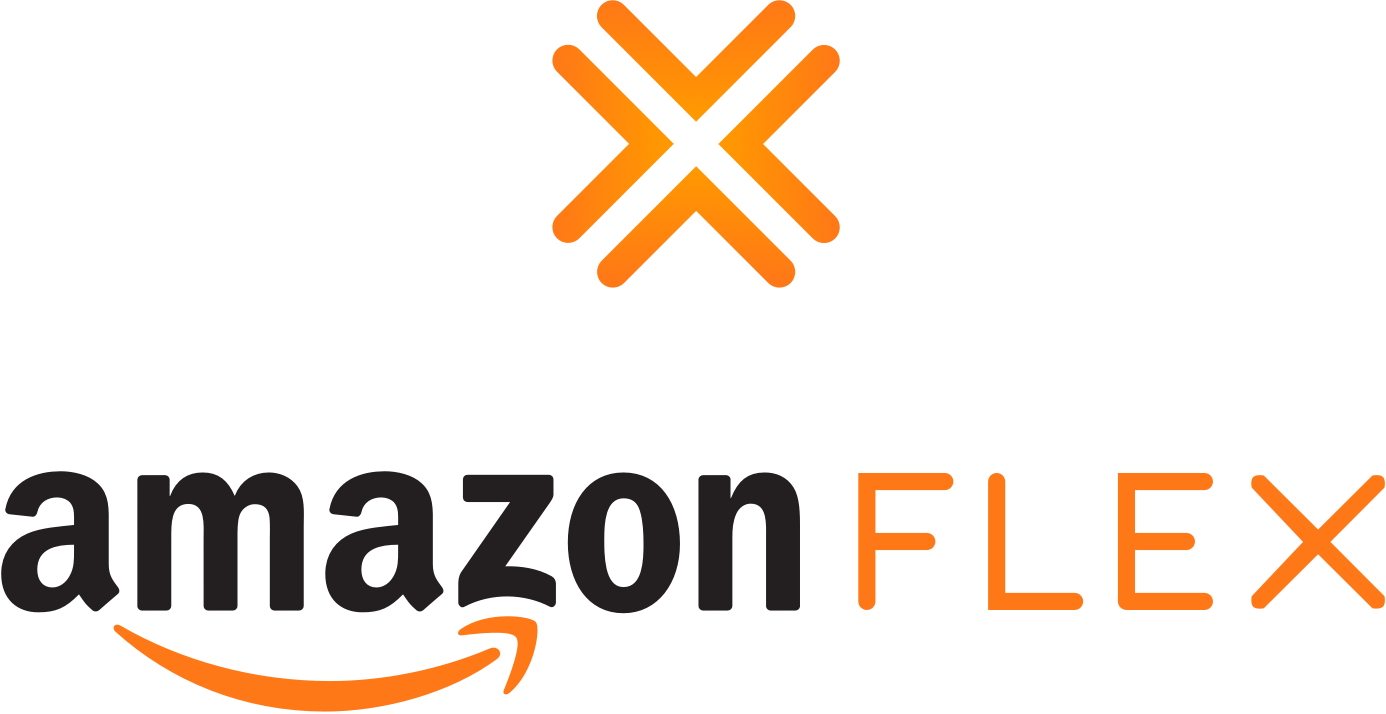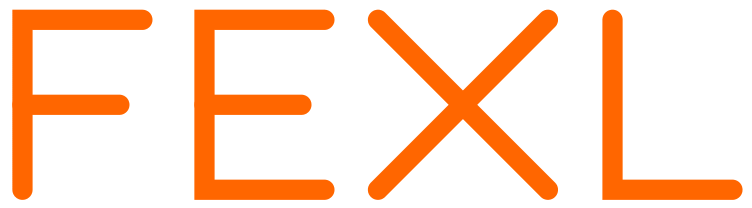
amazon FLEX – gestatetes Logo oder Font?
Gesucht wird FLEX, weiß jemand ob das auf einer Satzschrift beruht?
Sieht gestaltet™ aus. Die Rundungen wirken sehr angesetzt und das X ist irgendwie zu klein :-?
Konkretes kann ich aber nicht sagen ...
wobei Ecke oben links am E und im Kontrast dazu die Rundung unten links ... würdest du das machen, wenn du so ein "simples" Logo selbst baust? Ich such mal nach was Isometrischem, so wie der Miso ...
PS: wirklich weitergekommen bin ich da leider auch nicht ... :-?
Zumindest lässt sich das in kürzester Zeit ohne Font bauen
Das ist schon klar, hätte ich auch in zwei Minuten erledigt. Es geht aber um die restlichen Buchstaben und neu zu erstellende Wörter.
Und was meinst du, woher die EXTRAWURST kommt?
Musste nur noch die ganzen Satz-und Sonderzeichen und die Kleinbuchstaben erfinden, natürlich auch ß und ẞ :-)
Insgesamt stecken da jetzt 4 Stunden drin - Inklusive Trockenlegen meiner Tastatur, über die ich Mineralwasser gekippt habe :-( Dafür geht jetzt auch die 0 wieder, wie sie soll. War also ohnehin fällig.
Dass deine fliegenden Einhörner die fehlenden Zeichen in Windeseile herbeitragen war mir schon klar … :-D
Beim "Original" ist aber z.B. beim E links nur eine Ecke kantig, unten ist sie wieder rund. Oder möchtest du den "Abstand" lieber absichtlich beibehalten?
Nö, das hatte ich schlicht übersehen, dann gleich auch bei B und D unten gerundet.
Dann noch n bisserl OpenType, wie Tabellenziffern, hoch und tiefgestellte usw, Ligaturen, die ẞ-Automatik nach 2 Großbuchstaben oder zwischen 2 Großbuchstaben rein gepackt.
Und die Einhörner wieder auf die Koppel geschickt.